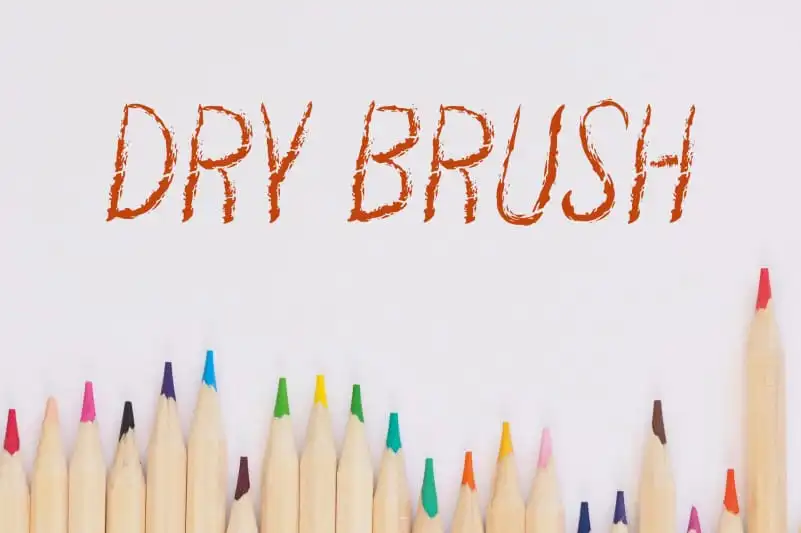
Dry Brush Font
Aqui está uma breve descrição para a página de download do Dry Brush Font, mantendo os requisitos: O Dry Brush Font é perfeito para aqueles que buscam um estilo artesanal e natural em suas designações digitais. Este tipo brush foi criado pelo designer Vladocar e possui linhas suaves e rústicas que imitam o esfregamento de um pincel, resultando em texturas interessantes e uma aparência autêntica. Ideal para aplicar em elementos gráficos como títulos de página, marcas digitais ou até mesmo para criar efeitos visuais impressionantes. Descubra a beleza simplória da natureza através deste design único e experimente incorporá-lo em seus projetos para adicionar um toque autêntico e vibrante à sua identidade visual. Com uma licença comercial, pode-se usar este font em ambientes de negócios ou publicações digitais sem restrições adicionais. Esta font é perfeita para quem busca incorporar elementos artesanais no seu trabalho gráfico, seja em design de arte digital, branding, logotipos ou até mesmo na criação de sites. Explore as possibilidades criativas do Dry Brush Font e decore seus projetos com a essência da natureza. O Dry Brush Font é uma excelente opção para aqueles que desejam adicionar um toque singular e autêntico em suas obras, reforçando a sua personalidade e estilo.